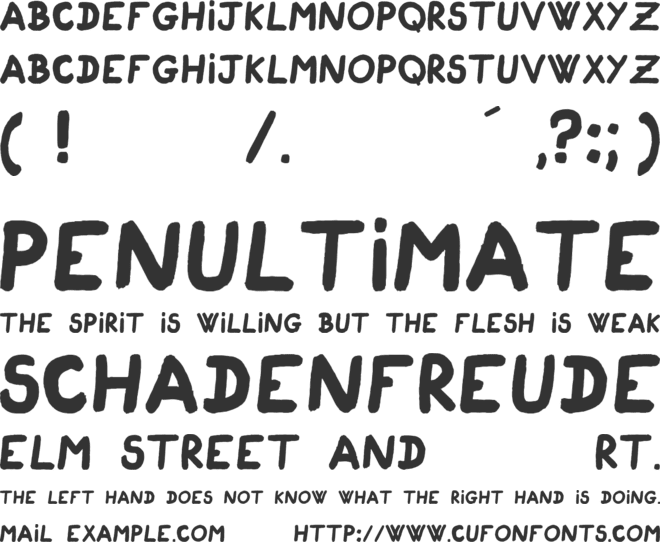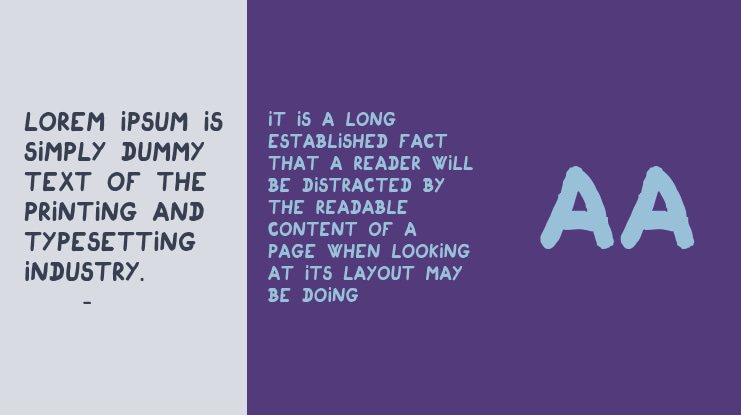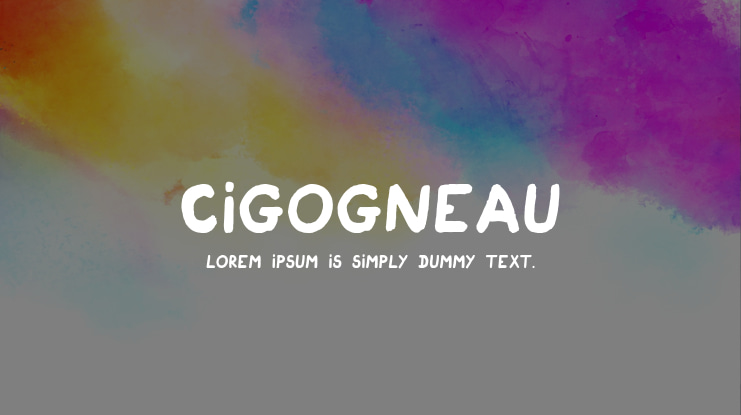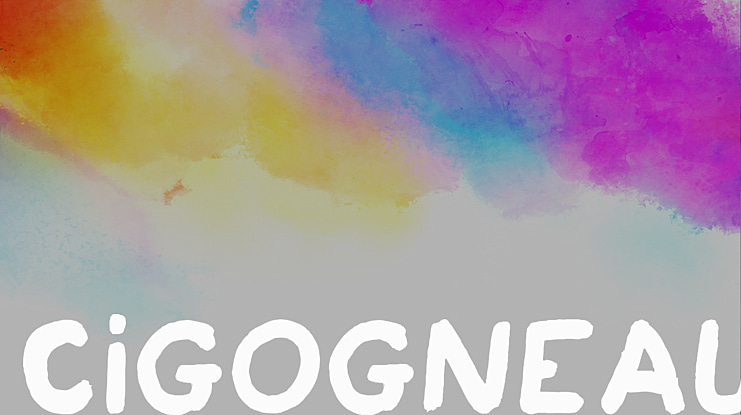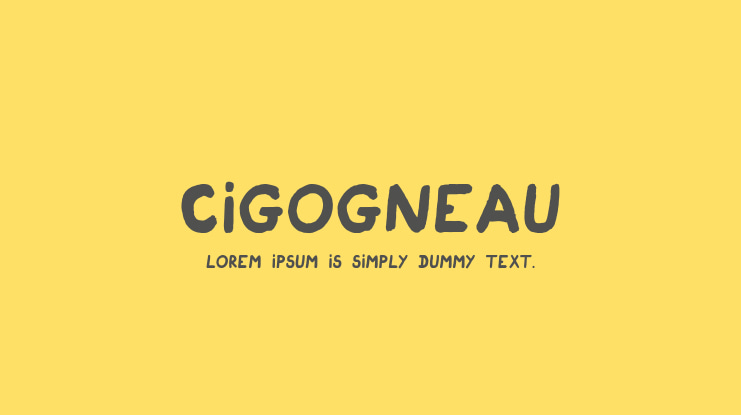
Cigogneau Font
Caractères manuscrits dessinés au pinceau et à l'encre de chine scannés. La Cigogneau, typo ronde et simple, est destinée à une utilisation dans le cadre du lettrage en Bande Dessinée.